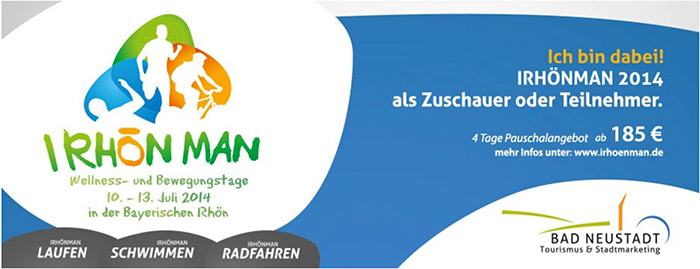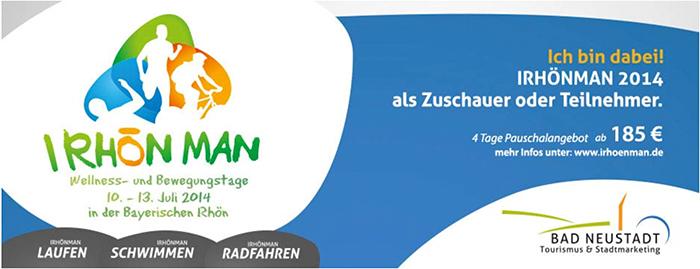
Die Könnten das Fahrrad ja wenigstens durch ein Röhnrad ersetzen, wenn sie schon Wortspielen wollen …
wau. na ja, vielleicht haben die ja das etwas ältere, gemächlichere publikum im auge. irgendwas müssen die ja drin haben. tatsächlich. eine echte bieridee. wau. take your rollator and röhn.
Ich finde übrigens, dass die Bildmarke wie eine Bildergeschichte aussieht: Ein Radfahrer fährt einen Jogger um, der daraufhin (ins Wasser) fällt.  :-|
Nachtrag: Es sieht übrigens irgendwie so aus, als würden die Sportler von rollenden Ostereiern verfolgt …  ;-)
Wäre es evtl. besser geworden, wenn man iRHÖNman geschrieben hätte? Ich habe ein wenig gebraucht, bis ich das seziert hatte ... Oder hätte sich dann iMac beschwert?
Interessant auch der Einsatz des Makrons über dem o.
Ich glaube, ich erwähnte es schon mal, dass ich mich bei einem Ladenschild "fon" mit Makron über dem o fragte, wie ich das zu interpretieren habe:
- wie bei n/m im Deutschen als Verdoppelung, also foon oder
- wie bei u/n zur Unterscheidung des u in Sütterlin & Co., hier als Unterscheidung des o vom ... ähm ...
(War übrigens ein Friseur, inzwischen mit anderem Ladenschild)